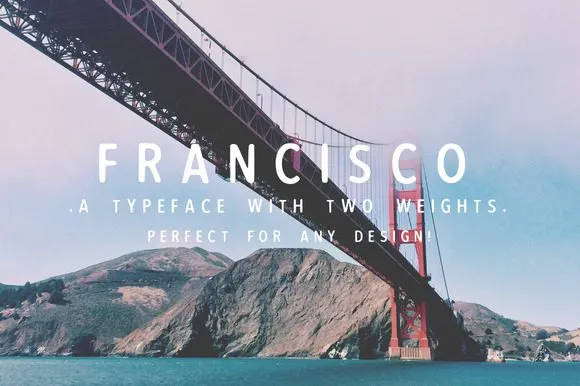
A fonte ‘Francisco’ é uma seleção elegante das duas pesos disponíveis nas famosas imagens únicas capturadas por Pierre Rougier. Inspirado na beleza vibrante e desafiadora das fotografias de Pierre, a fonte ‘Francisco’ oferece um toque moderno e versátil que combina perfeitamente com os estilos de design contemporâneos. Sua simplicidade e facilidade de leitura tornam-a uma escolha ideal para aplicações em sites e aplicativos digitais, mantendo-se à vanguarda do design de fontes modernas sob o supervisão da designer Hamilton. Com um toque sofisticado que se adapta perfeitamente a qualquer projeto gráfico, ‘Francisco’ é uma ótima adição para designers de todos os níveis que buscam uma alternativa moderna e eficaz às fontes convencionais.